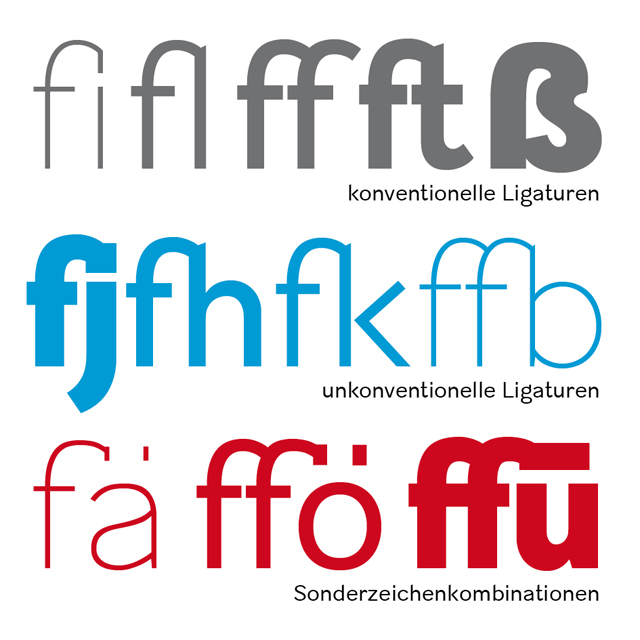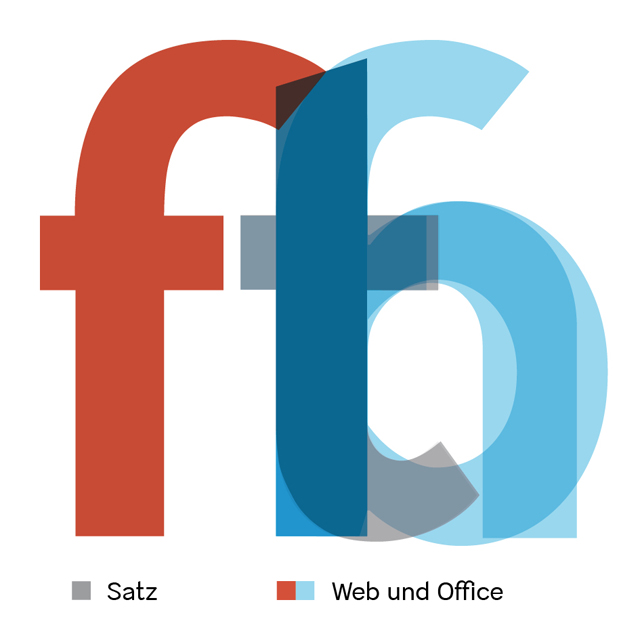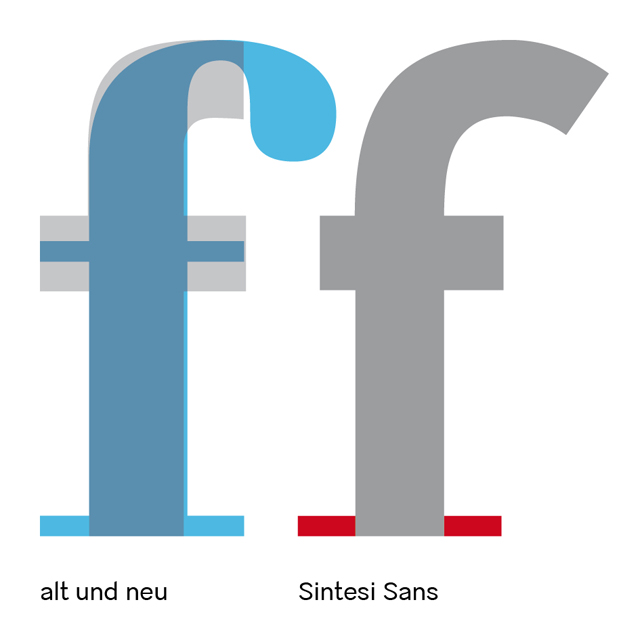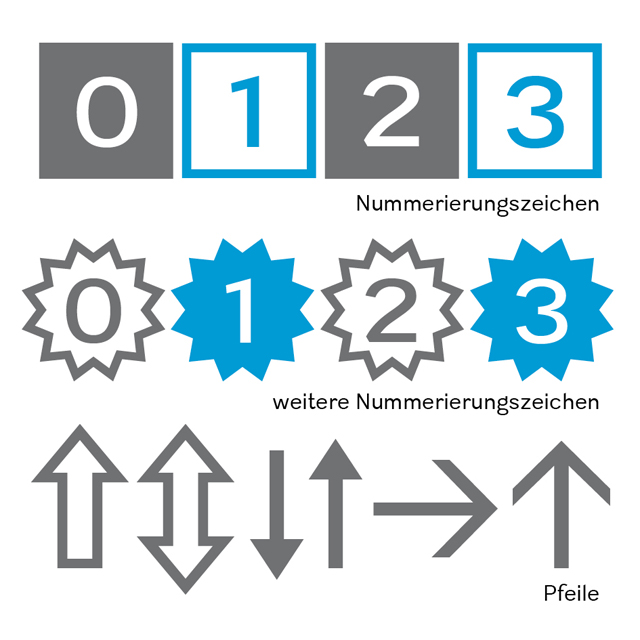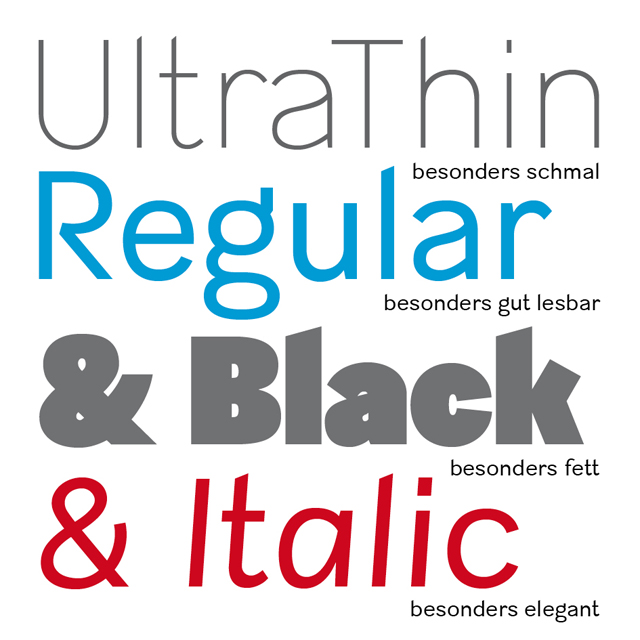
Sintesi Sans. Serifenlose trifft auf Serifen.
Ligaturen sind typografische Raffinessen für Kenner. Darunter versteht man die Verschmelzung zweier oder mehrerer Buchstaben zu einer Glyphe. Sie helfen, optische Lücken zu vermeiden, die den Lesefluss hemmen. Lange waren Ligaturen den Serifen-Schriften vorbehalten. Heutzutage erleben sie eine Renaissance und tauchen vermehrt auch unter Serifenlosen Schriften auf. Die Schrift Sintesi Sans ist mit einer grossen Auswahl an Ligaturen ausgestattet, die weit über übliche Kombinationen zwischen den Buchstaben «i», «f» und «l» hinausgeht.
Die Unzulänglichkeit der digitalen Medien erlaubt bis heute keinen medienübergreifenden, konsistenten Einsatz von Ligaturen. Dank eines innovativen Ansatzes ist es Sintesi Sans als einziger Schrift gelungen, eine beinahe konsistente Erscheinung quer durch alle Medien zu gewährleisten, sowohl im gepflegten typografischen Satz auf Papier, als auch im Web oder in einer Office Umgebung. Möglich wurde dies durch eine spezielle Zurichtung der Schrift Sintesi Sans. Diese erlaubt auch die Verwendung der eleganten, traditionellen Form des Kleinbuchstabens „f“ mit grossem Überhang, wie man sie sonst nur bei Serifenschriften findet.
Sintesi Sans verfügt zudem über eine immense Auswahl von speziell zugeschnittenen Nummerierungszeichen und Pfeilen.
Zu den Stärken der Schrift Sintesi gehört eine besonders elegante Kursive, die dank ihrer moderaten Schriftlage zu weit mehr als nur zu Hervorhebungszwecken genutzt werden kann.
Beweisen Sie Ihre typografische Kompetenz, mit Sintesi SemiSans.
Mal abgesehen davon, dass mich das penetrante Eigenlob nervt, finde ich diese Schrift absolut nicht überzeugend. Die Sans mag (aber nur in den leichteren Schnitten) ja vielleicht noch gehen, die SemiSans und die andere finde ich völlig verunglückt. Dieses Mischen von Sans mit Serif ist schon bei anderen (Rotis, Thesis) nicht unbedingt immer glücklich gelungen, hier ist es m.E. völlig schiefgegangen, soweit man das überhaupt beurteilen kann nach den Bildern auf der Website. Die Sintesis in fetteren Schnitten hat für mich komischerweise sogar eine gewisse 50er Jahre-Anmut bekommen, ich weiß aber nicht, woran das liegt. Die maniriert drangesetzten Serifen hauen dermaßen rein, daß ich mir Leserlichkeit, gescheite Grauwerte oder wenigstens schöne Wortbilder aus der Schrift überhaupt nicht vorstellen kann. Zeitgemäß und elegant ist diese Schrift bestimmt nicht, wie robust sie ist kann ich nicht einschätzen.
… Wir wollten aber über die schöne Schrift reden, mit deren typografischen Raffinessen …
Wollten wir? Dann wollen wir mal …
Die rot hervorgehobene Aussage kann ich schon mal als nicht zutreffend bezeichnen, wenn ich mir die Umlaute in der fetten Überschrift so anschau …
mit deren typografischen Raffinessen
die man auf der Website gar nicht sieht: kein Glyphenüberblick, keine wirklich aussagekräftigen Beispiele wie die Schrift wirklich läuft, keine Möglichkeit mal ein Wort einzugeben um zu sehen wie es aussieht ...
Worüber sollen wir also reden?
Dafür aber hier im Forum oberlehrerhafte Belehrungen verbreiten über Ligaturen, die teilweise nicht einmal stimmen (es gibt schon gaaaanz lange Ligaturen in serifenlosen Fonts).
In der angehängten, leicht unverständlichen Grafik sind Beispiele für "Ligaturen" (unter dem Begriff Sonderzeichenkombinationen) wie sie eigentlich eben nicht sein sollten und auch nicht gebraucht werden.
Ob eine weniger schräge Kursive nun "besonders elegant" ist - darüber gibt es zu Recht sehr unterschiedliche Meinungen.
Die Buchstabenformen kann ja vielleicht ein Experte hier mal im Detail auseinandernehmen, ich persönlich finde etliche unmöglich ... und man sieht ja nicht einmal alle Zeichen.
Bei grösseren Schriftgraden entfaltet sie ihren traditionellen Charakter. Nun kommen ihr starker Strichkontrast und der spürbare Feder-Duktus voll zur Geltung, wie es sich für eine geschichtlich verwurzelte Antiqua gehört. Vereinen Sie die Antike mit der Moderne!
Blasen über Blasen. Was ist ein "traditioneller Charakter" in so einer Schrift? Wo ist da ein Feder-Duktus? Was ist eine "geschichtlich verwurzelte Antiqua? Und wer bestimmt, was sich dieser "gehört"? An der "Vereinigung von der Antike mit der Moderne" hat sich eben schon mancher verhoben ...
Was ich - ohne forschen und entdecken - sehe, motiviert mich leider nicht genug, weiterzugraben. Da sind gewisse "Show-Stopper" drin, die vermutlich auch durch das spätere Entdecken von Rafinessen nicht überstahlt würden.
Soweit ich mich erinnere hatten wir auch schon damals im Zuge der Namenssuche zur Schrift Zweifel an bestimmten Details angemeldet, aber für Detailkritik ist es jetzt vermutlich eher zu spät.